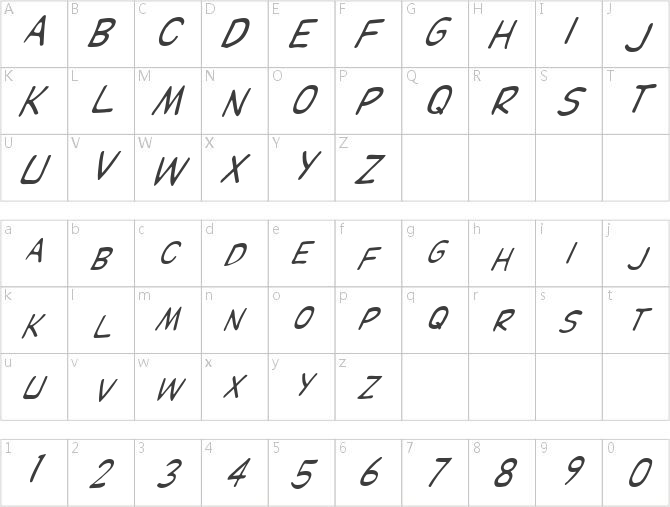
FZ BASIC 29 ITALIC
FZ BASIC 29 ITALIC介紹
FZ BASIC 29 ITALIC字體字庫(kù)是一款讓人賞心悅目、百看不厭的英文字體,適合各類廣告和產(chǎn)品包裝設(shè)計(jì)應(yīng)用,字體大小0.05MB,格式為ttf字體,上傳用戶是dqq520,作者/版權(quán)方為未知